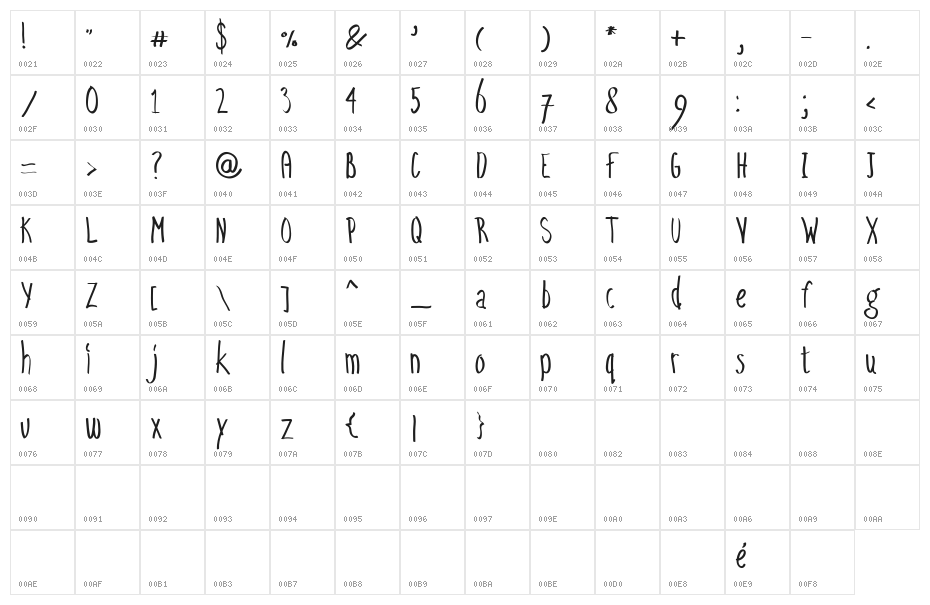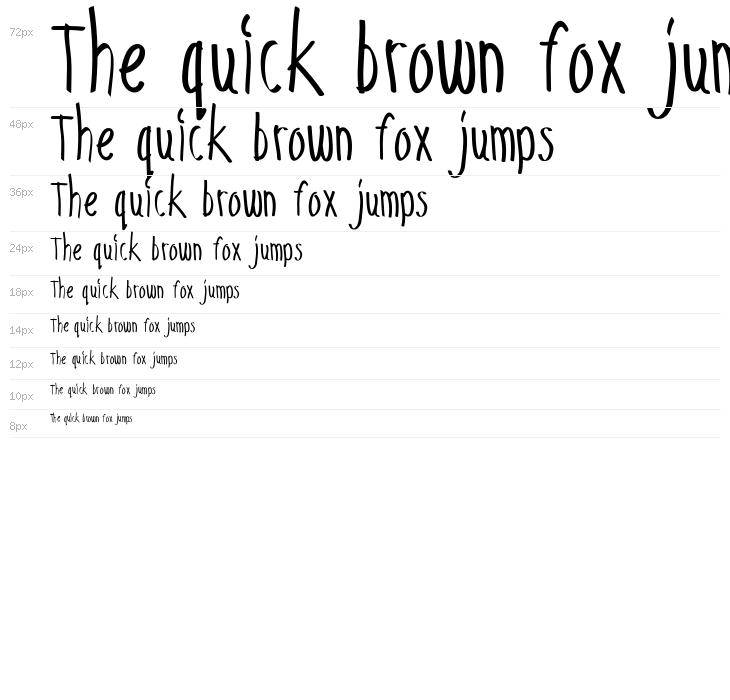
Easy GoingRegular Font
| Stile generale | Casual |
| Caso d'uso | Logos, Headlines, Informal Text |
| Progetti proposti | Ideal for greeting cards, children's books, casual branding, and playful social media graphics. |